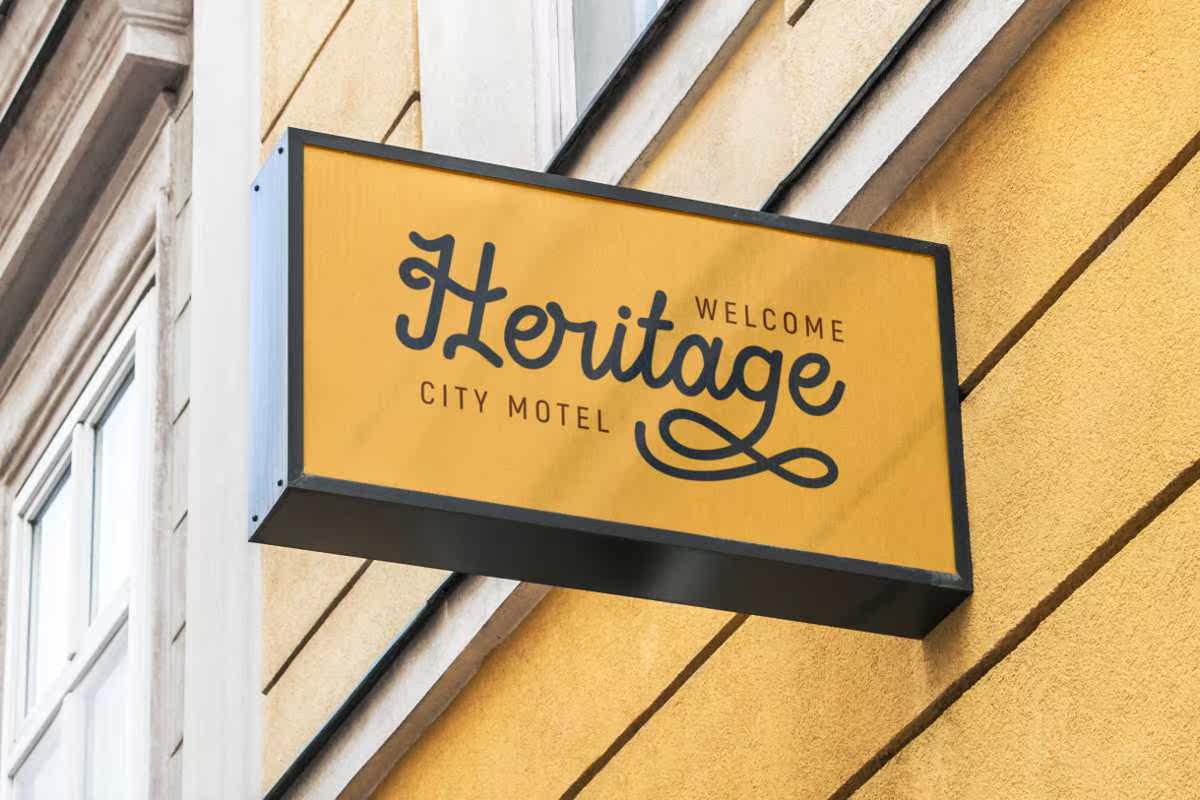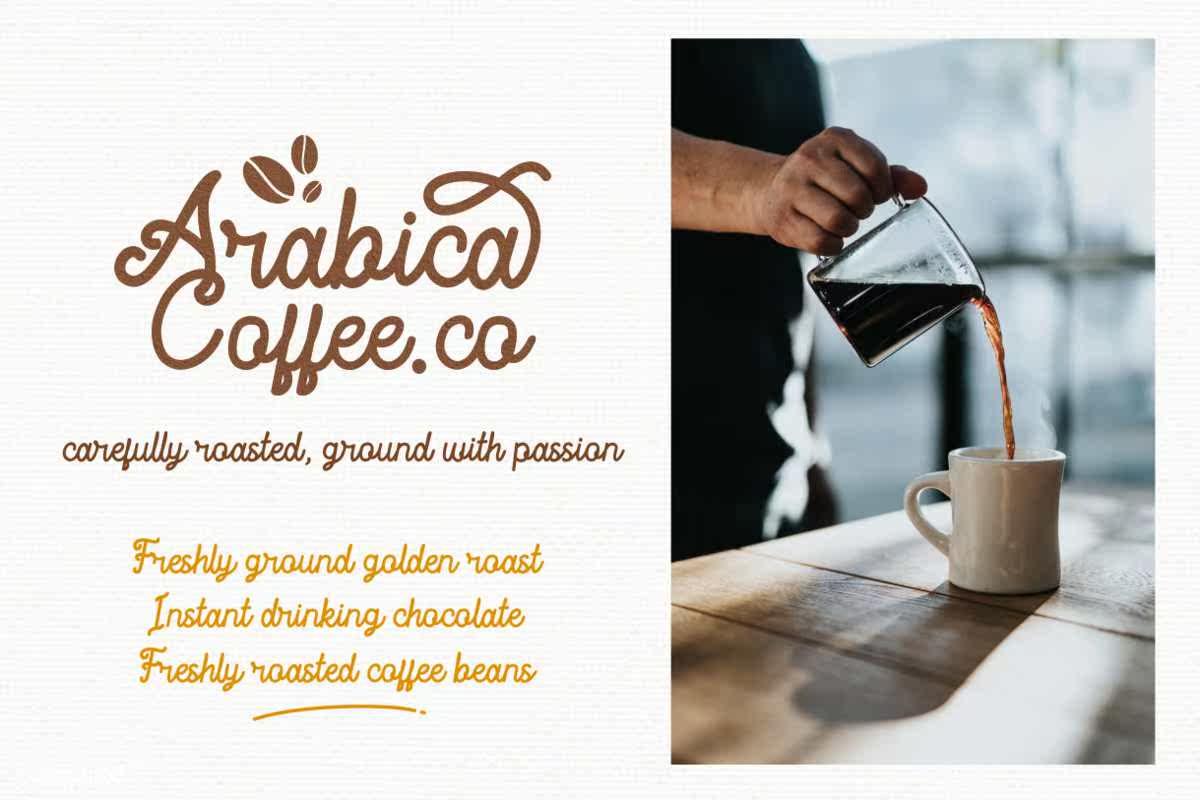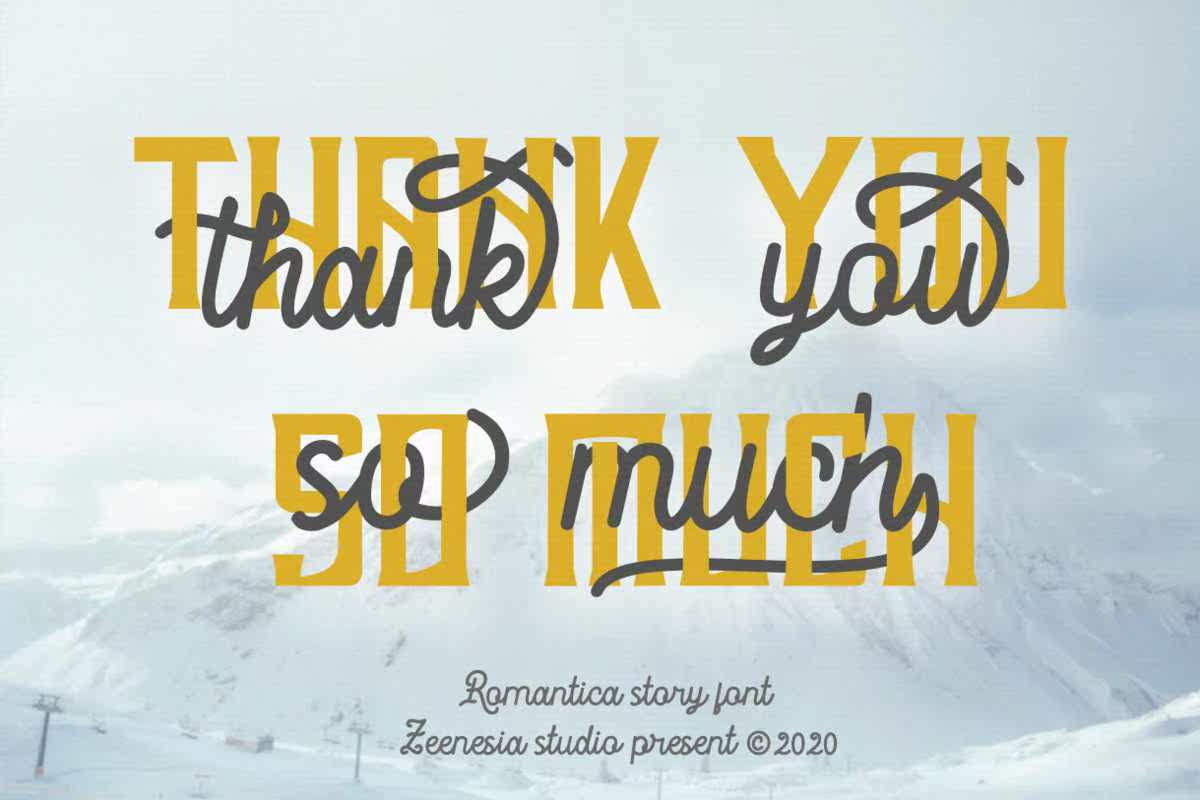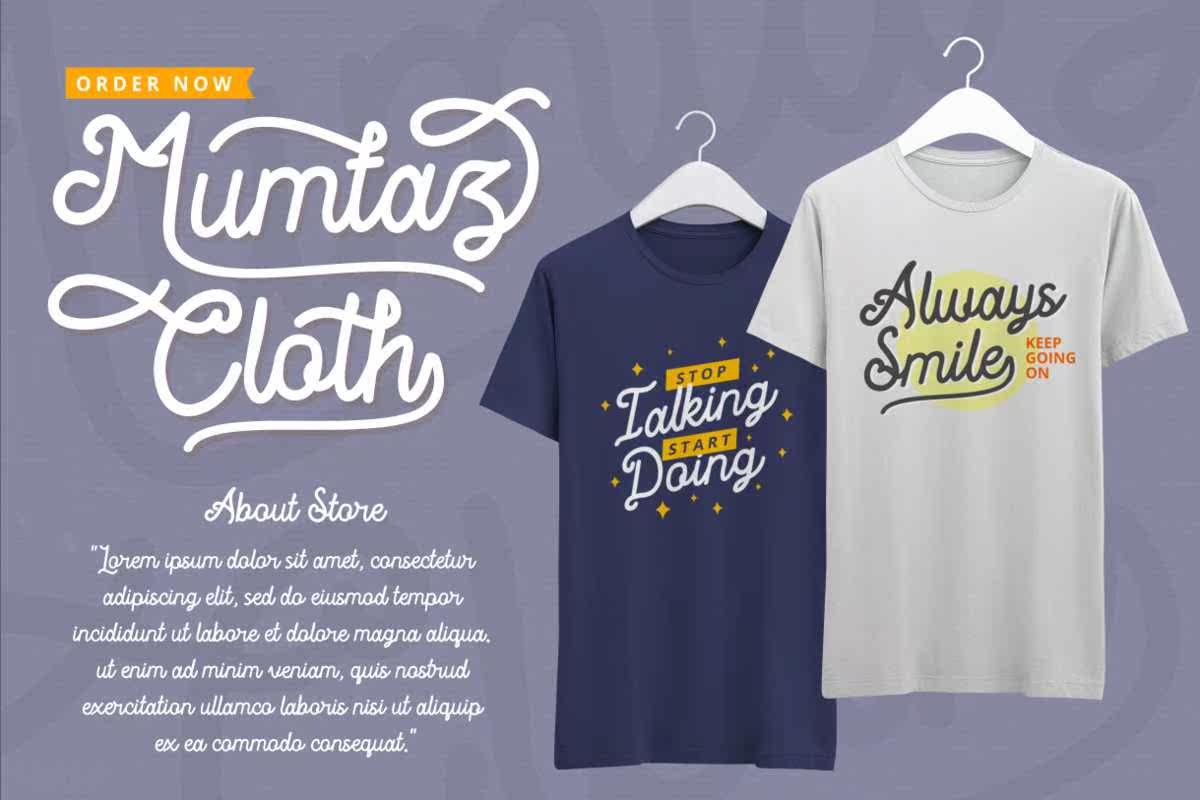
RomanticaStoryScriptFont是一个多字体的单线脚本Font。它包括大写、小写、连字、文体替换、swash和支持多语言。RomanticaStoryScriptFont适用于徽标、品牌、问候卡、报价、包装、海报、广告、名片、网站、设计标题、博客标题、艺术报价、排版、邀请、服装、摄影、,婚礼、标签和其他需要独特奢华触感的设计。Romantica Story Scription Font是一款具有大量情景的单线Scription Font。它包括大写、小写、连字、文体替换、swash和支持多语言。Romantica Story Font适用于徽标、品牌、问候卡、报价、包装、海报、广告、名片、网站、,设计标题、博客标题、艺术报价、排版、邀请函、服装、摄影、婚礼、标签以及其他所有需要独特奢华触感的设计。